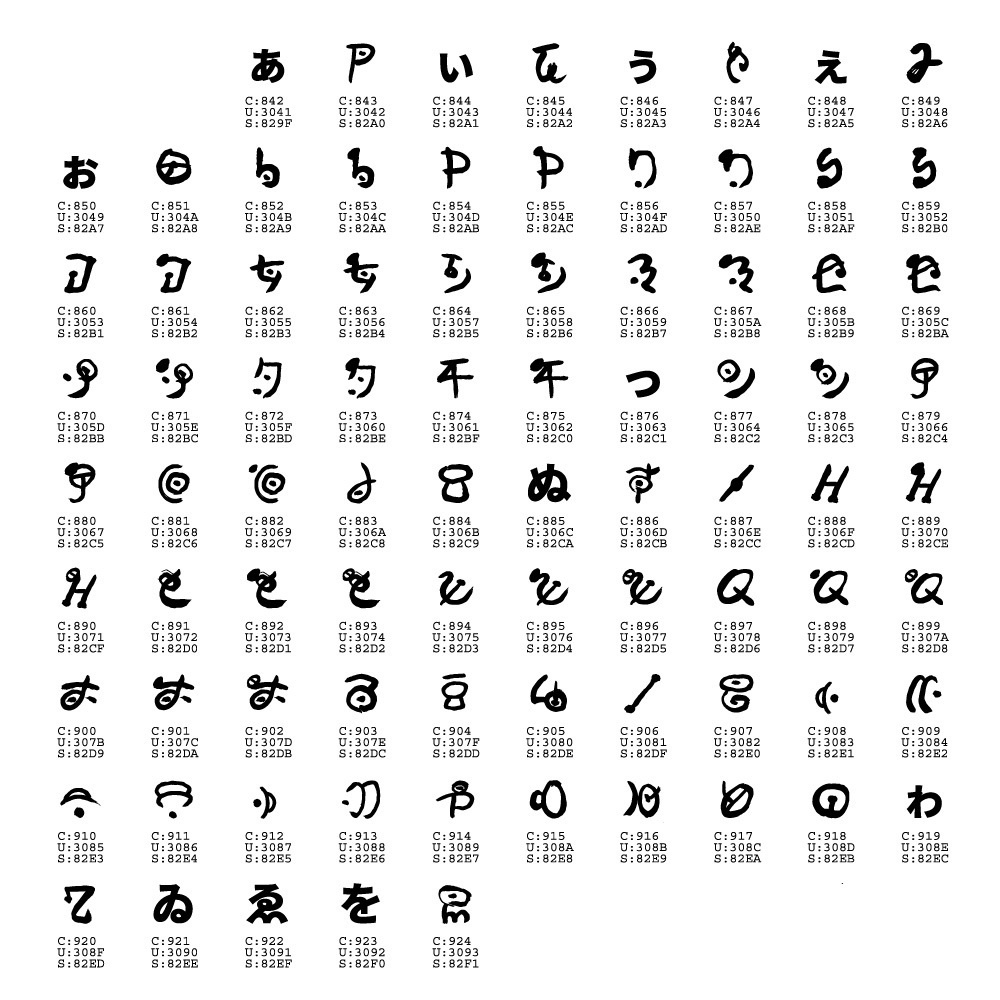
フリーフォント「奈落文字」
祝!メイドインアビス 2期! 作中にて登場する「奈落文字」を手書き風フォントで再現しました。 源ノ角ゴシックをベースに全角ひらがなと一部記号を奈落文字に変えております。 原作者にファンレターを送りたい時なんかにお使いください。 「無料ダウンロード」と「投げ銭」でデータの違いはありません。 ご支援いただける方のみ「投げ銭」からダウンロードお願いいたします。 このフォントは、源ノ角ゴシックをベースにメイドインアビスに登場する奈落文字を模したものになります。 公の場で使用し、何かしらの不利益を被ることがあっても当方は責任を負いかねます。 ご理解頂けた方のみ、自己責任でご使用ください。 ※「ぬ」「を」などのまだ解読されていない文字はひらがなのままです。 ※商標登録する、作者を偽る、フォントデータ自体を二次配布または販売や転売する改変する行為は禁止です。 ※このフォントは、オープンソースフォントである「源ノ角ゴシック heavy」を使用しています。 ※文字の解読は、スルダ@surudar さんの奈落文字読解表を参考にさせていただきました。 https://mobile.twitter.com/surudar ●概要 Format: OpenType Licence: フリー 誤動作・誤出力などフォント使用に伴ういかなる問題も、当方は責任を負わないものとします。ご自身の判断のもとお使いください。 Congratulations! Made in Abyss Phase 2! The "Narakuji" that appears in the work has been reproduced in a handwritten style. Based on Source Han Sans, full-width hiragana and some symbols have been changed to abyssal characters. Please use it when you want to send a fan letter to the original author. This font is based on Source Han Sans and imitates the abyss characters that appear in Made in Abyss. We are not responsible for any disadvantages caused by using it in public. Please use only those who understand. * Undeciphered characters such as "nu" and "o" remain in hiragana. * It is prohibited to register a trademark, disguise the author, distribute, sell or resell the font data itself at 2 o'clock. * This font uses the open source font "Source Han Sans heavy". * For deciphering the characters, I referred to Suruda @surudar's abyssal reading comprehension table. https://mobile.twitter.com/surudar ● Overview Format: OpenType License: Free